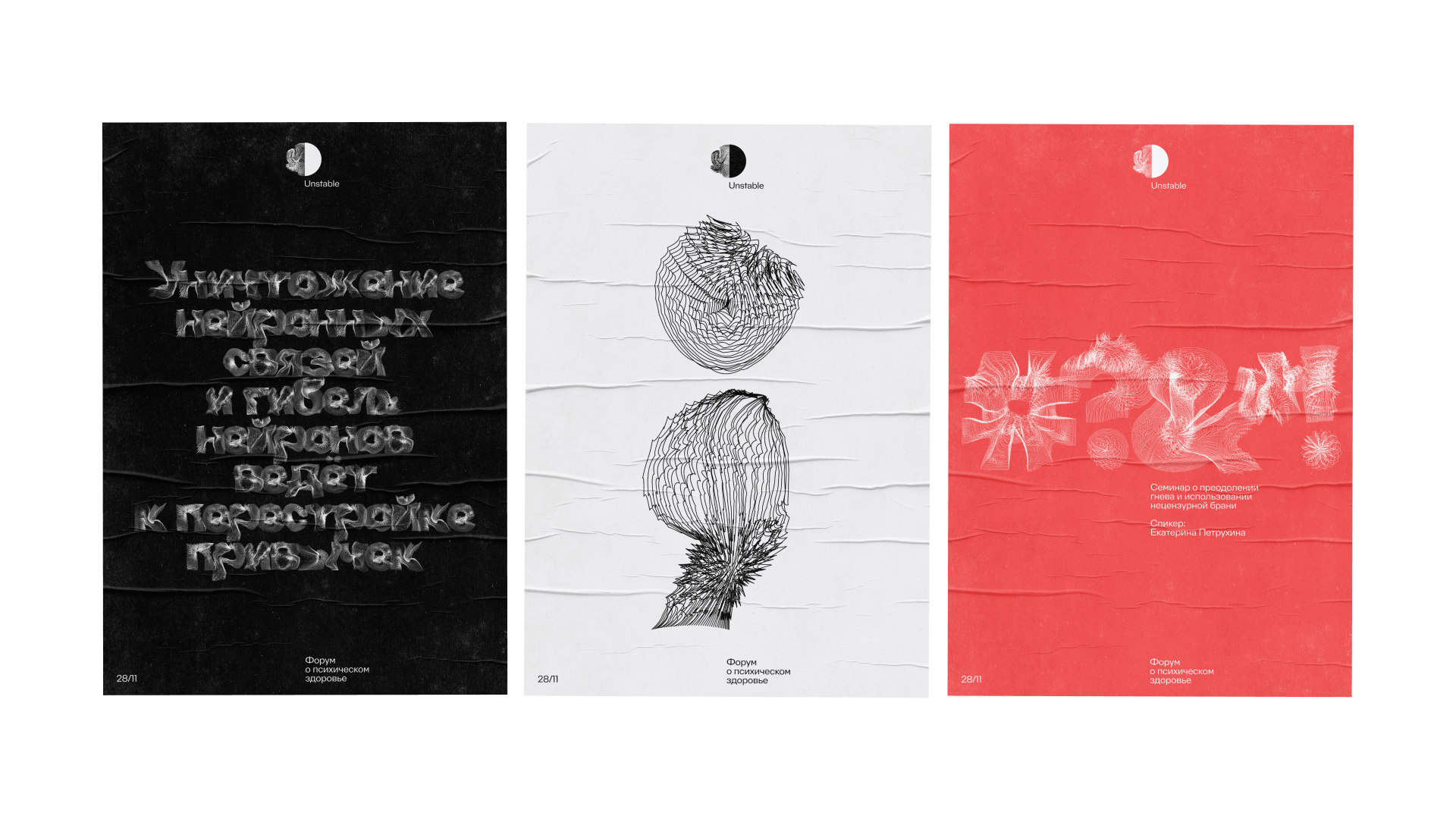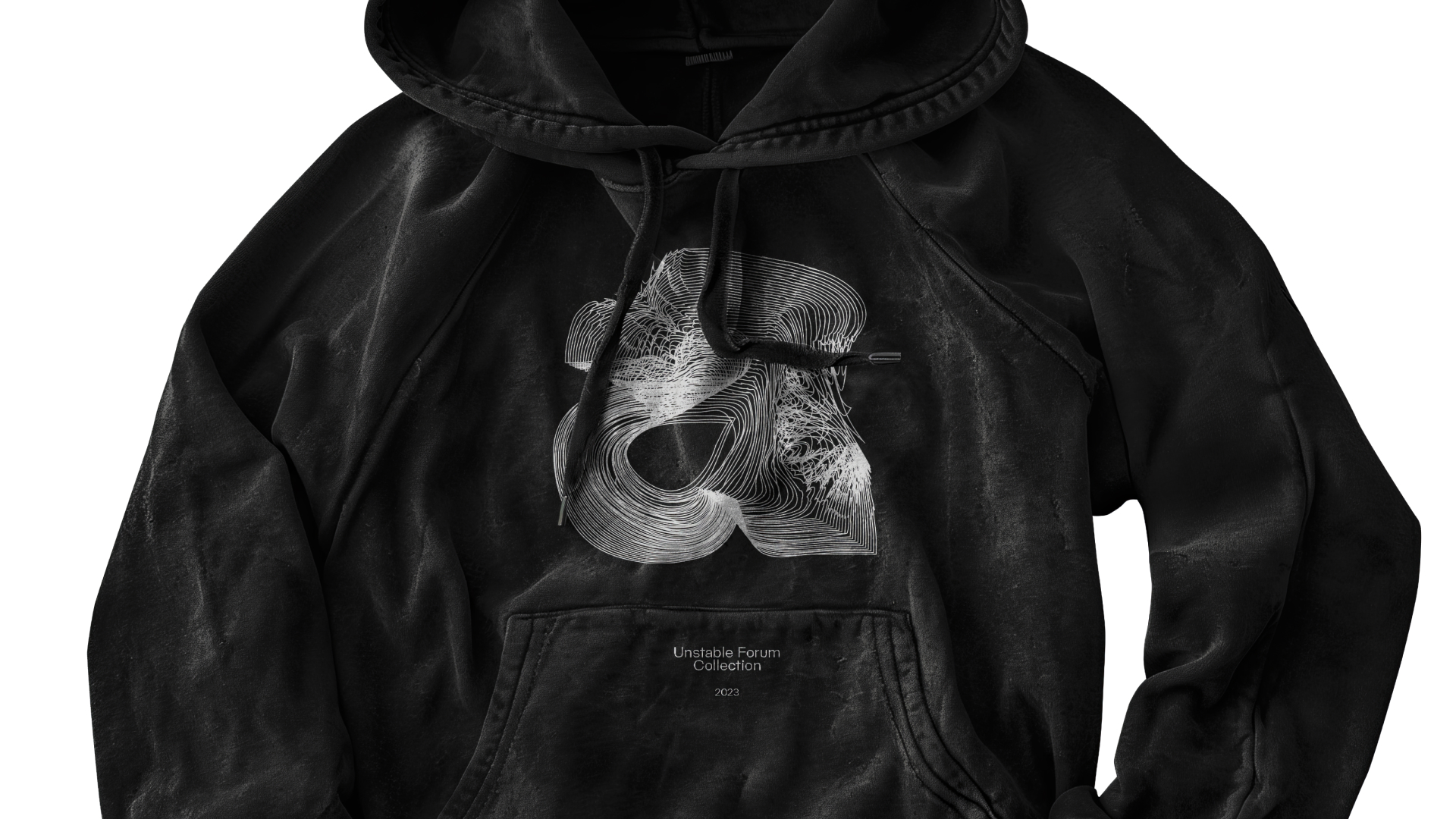
Тиражный шрифт
Tearing Font
Описание работы
Шрифт Tearing основан на метафоре уничтожения нейронов во время стрессовых ситуаций. Он состоит из контуров, которые «повреждены»; части букв растягиваются, рвутся и приобретают новую форму, отсылая к разрушению нейронных волокн.
Множество букв шрифта имеют вмятины, следы от ударов, отсылающих к стрессу, физическому и эмоциональному насилию, становящимися частыми причинами психических проблем. Кроме того, разные части букв имеют разную плотность, сжимаясь в густой комок — похожим образом умирают нейроны; а буквы при наборе соединены между собой, потому что все нейроны связаны между собой.
Шрифт был разработал для айдентики Unstable — форума о психическом здоровье. Айдентика форума отражает изменчивое состояние человека, имеющего психологические проблемы.